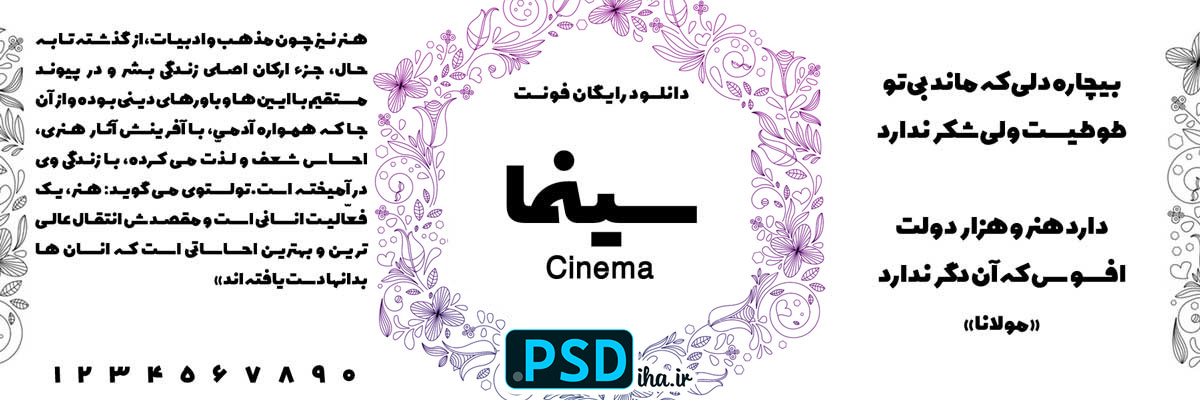
دانلود فونت سینما رایگان
فونت سینما
اگه از اون دسته طراح‌هایی هستید که عاشق بوی قدیمی سینماهای تهران قدیمید – همونایی با بلیت‌های کاغذی و پوسترهای رنگارنگ – فونت سینما دقیقاً براتون ساخته شده. من خودم تو پروژه‌های چاپی‌م، از تراکت‌های تبلیغاتی گرفته تا کارت‌های ویزیت خلاقانه، بارها سراغ این فونت رفتم و هر بار انگار یه تیکه از خاطرات بچگی‌م رو زنده می‌کرد. طراحی ضخیم و پرجلوه‌ش، با اون انحناهای نرم و خوانایی بی‌نقص، حس نوستالژیک سینمای کلاسیک ایران رو مستقیم به طرح‌هاتون می‌ریزه. تصور کنید لوگوی یه کافه سینمایی یا لیبل یه DVD کلاسیک با این فونت – مخاطب‌ها فوری می‌گن “وای، این دیگه چقدر باحاله و آشنا!”
چرا فونت سینما ستاره پروژه‌های چاپی شماست؟
این فونت نه تنها ضخامت‌ش چشم‌نوازه و تو تیترها و متن‌های بزرگ می‌درخشه، بلکه خوانایی‌ش تو اندازه‌های کوچک هم عالیه – ایده‌آل برای چاپ روی کاغذهای نازک یا براق. طراحان حرفه‌ای مثل من، ازش برای پوسترهای تبلیغاتی، کارت‌های دعوت، تراکت‌های فرهنگی و حتی لیبل‌های محصولات نوستالژیک استفاده می‌کنن. با نرم‌افزارهایی مثل ایلاستریتور یا این‌دیزاین، بدون هیچ مشکلی رندر می‌شه و تو چاپ نهایی، رنگ‌ها و لبه‌ها مثل یه فیلم سیاه‌سفید رنگی‌شده، زنده و واقعی درمیان.
فونت سینما با طراحی ضخیم و یکپارچه، همه نیازهاتون رو پوشش می‌ده – از تیترهای درشت که حس هیجان فیلم‌های دهه ۵۰ رو می‌دن، تا متن‌های حمایتی که بدون خستگی خونده می‌شن. انحناهای نرم‌ش، الهام‌گرفته از پوسترهای سینمایی قدیمی، یه لایه احساسی به کار اضافه می‌کنه بدون اینکه شلوغ بشه. اگه می‌خواید طرح‌تون حرف بزنه و خاطره بسازه، این فونت معجزه می‌کنه!